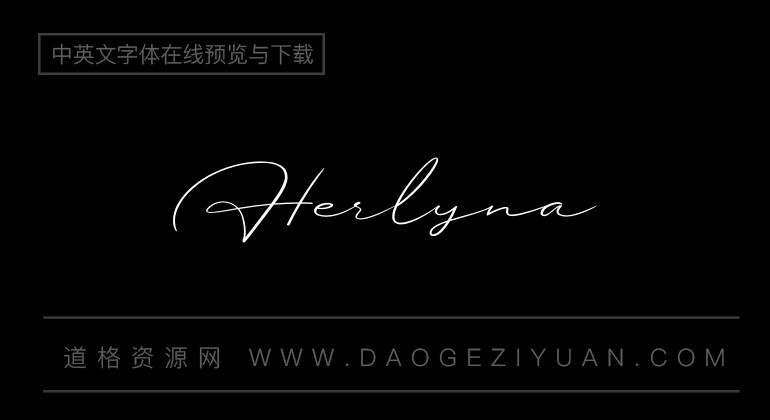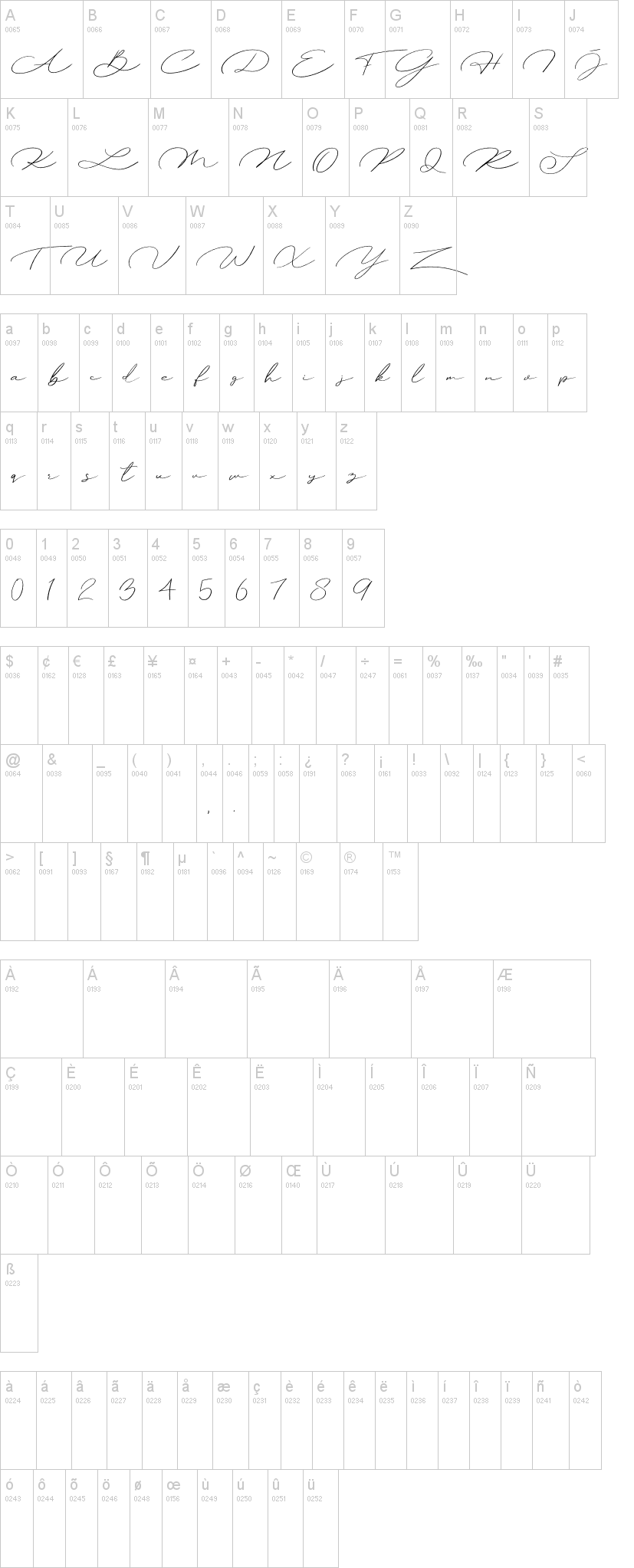
? Herlyna 字体是一款简洁大方的英文字体,由荷兰设计师 Herlyna 创作。这款字体采用现代风格,字体线条清晰,细节极其精细。它具有细腻的线条,给人留下清新、舒适的感觉。Herlyna 字体的字形设计极具特色,能够突出文字的细节,同时也具有良好的可读性。它适合用于各种文档、广告、海报等,可以展现出极具个性的设计风格。内容介绍
Herlyna是一款非常不错的手写艺术字体,具有很好的视觉感,适合于文化类的宣传设计、商业类品牌的广告和产品包装设计以及个性化文字排版等较多场景。